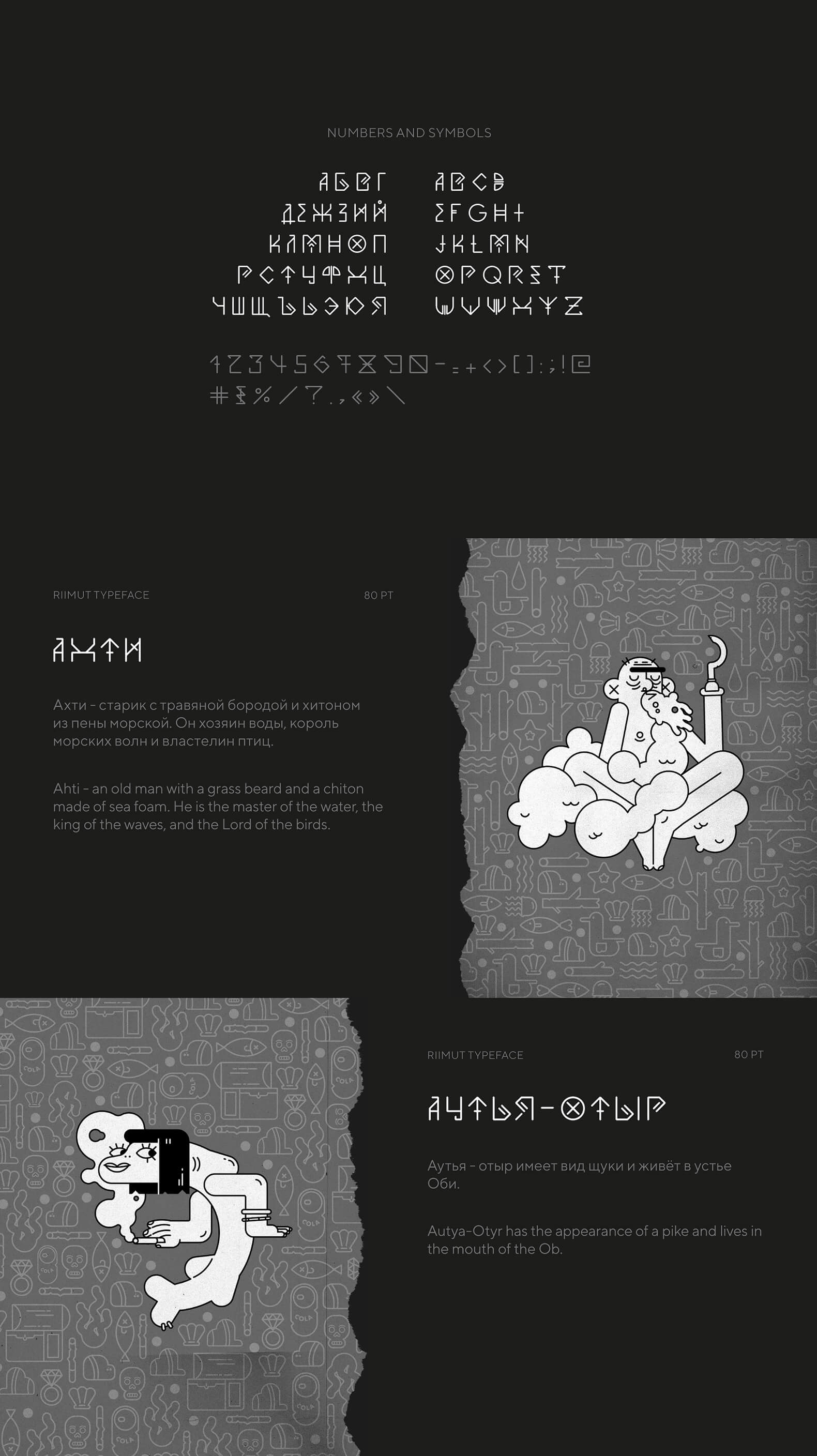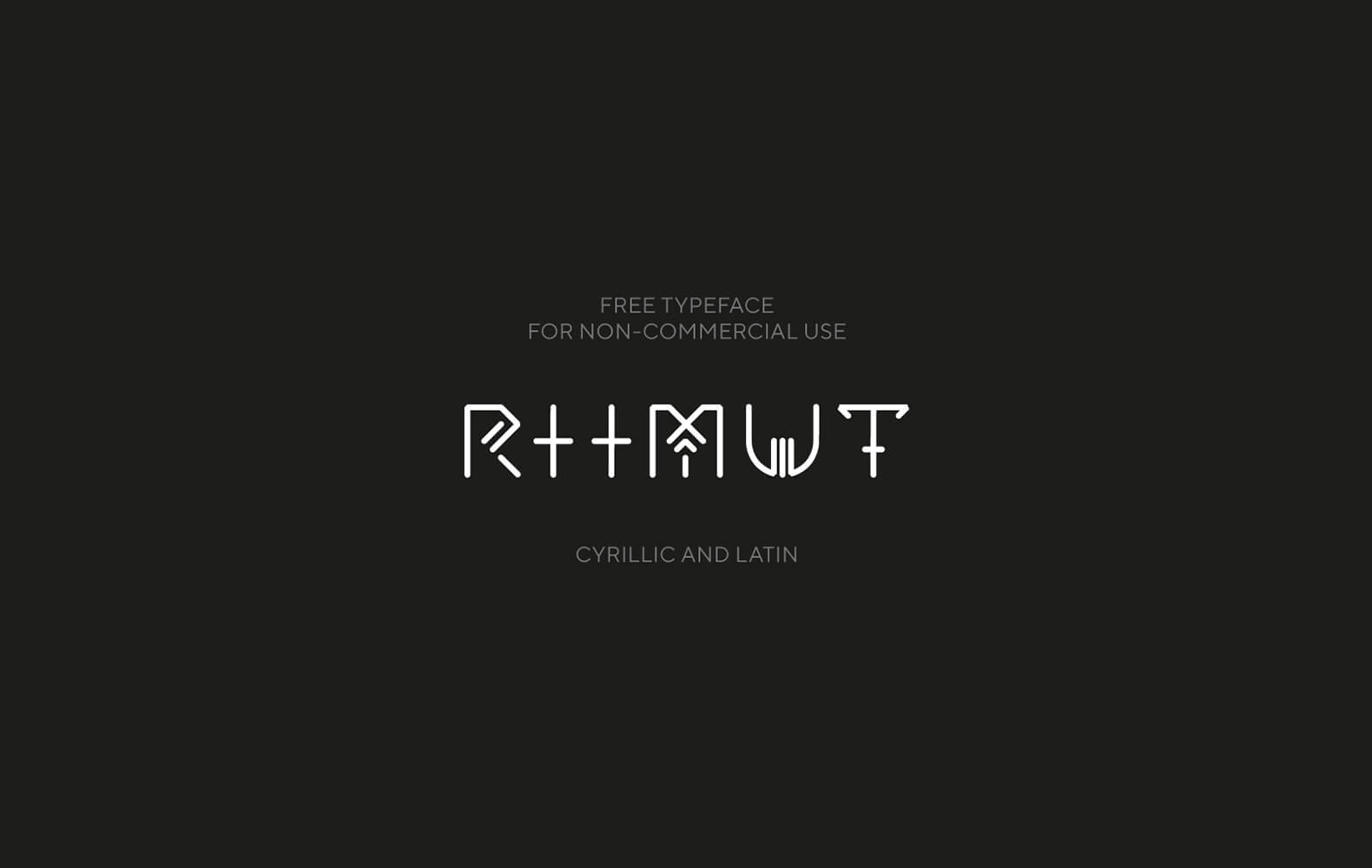
Шрифт — Riimut (Кириллица/Латиница)
Riimut — это акцидентный шрифт вдохновлённый финно-угорской мифологией. гарнитура состоит из латинского и кириллического набора знаков.